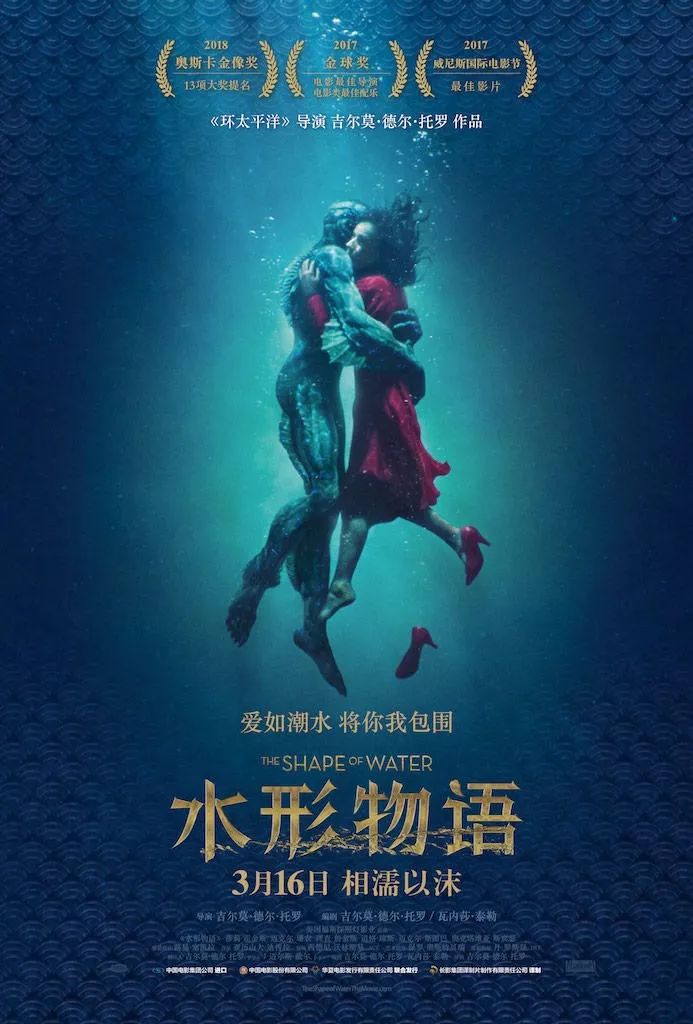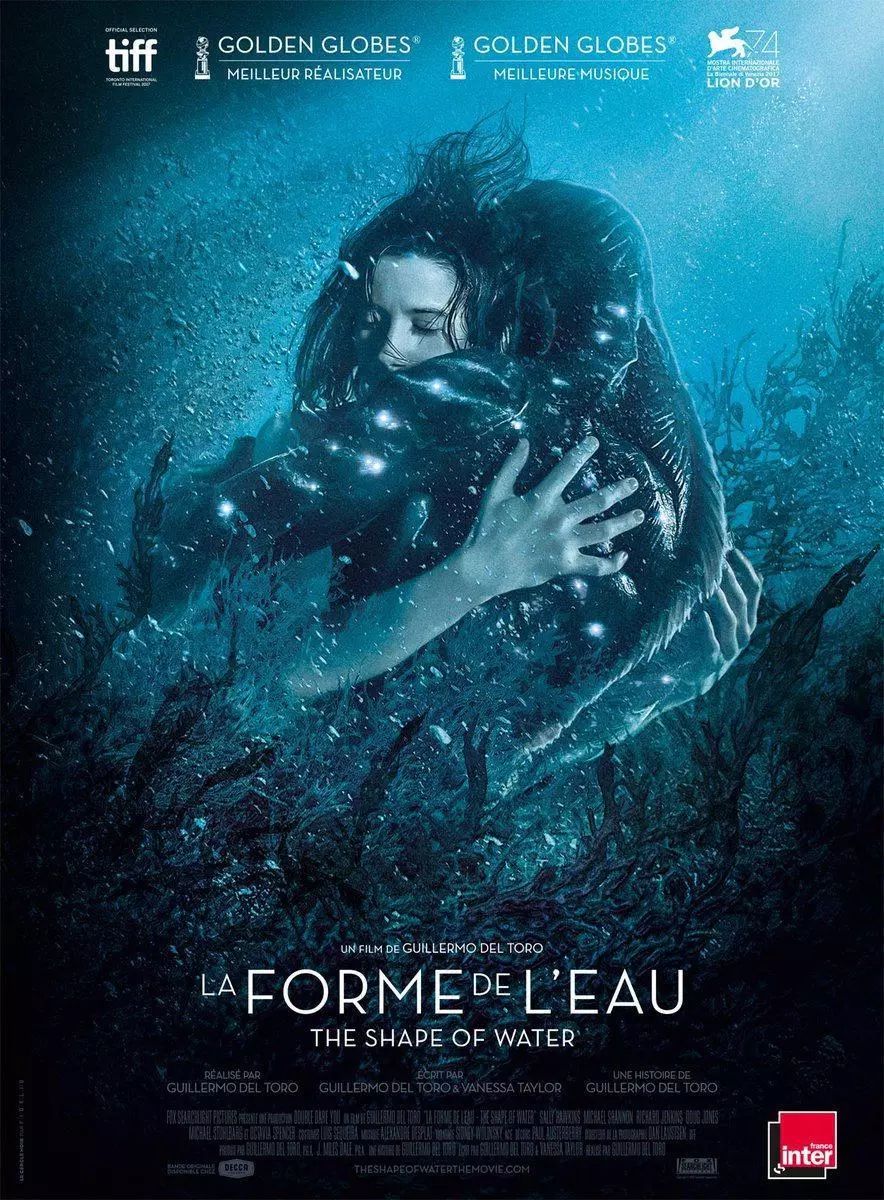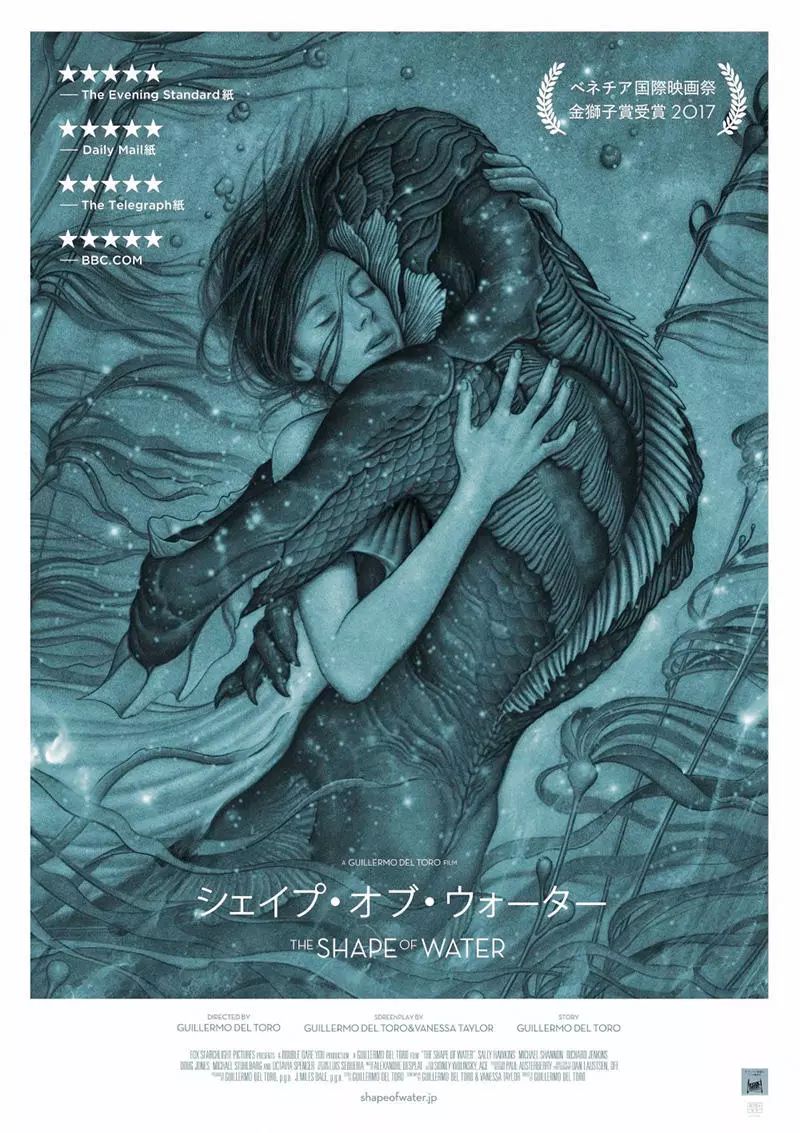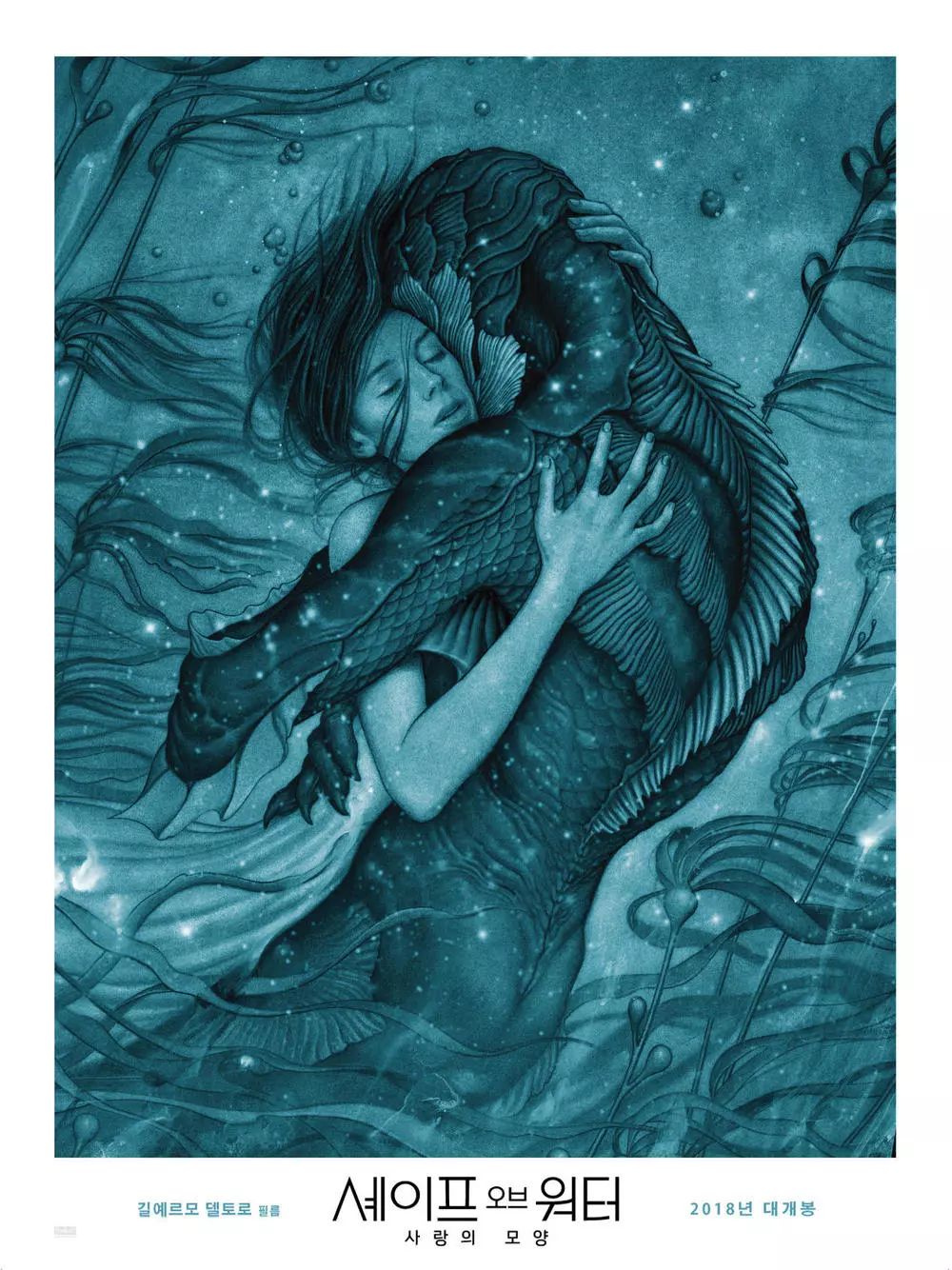
水形物语未删节版这个细节看过才会懂
要说谁是第90届奥斯卡金像奖最大的赢家?毫无疑问的是《水形物语》,《水形物语》以13项奖项提名领跑今年的第90届奥斯金像奖,该片获得了最佳影片、最佳导演、最佳电影配乐和最佳艺术指导4项大奖!
《水形物语》是奥斯卡历届最佳影片中最快引进中国的电影,3月5日奥斯卡颁奖盛典获封最佳影片,3月16日登陆中国院线。
WAIT~~
为什么小编看着这个海报~总觉得哪里不太对…..
于是小编去搜罗了一下各个国家《水形物语》上映的电影海报!
正式版海报——法文
正式版海报——日文
正式版海报——韩文
正式海报——俄文
英文原版海报
小编发现各个国家的海报应用都是无衬线字体,背景画面与文字相融合呼应,使整个画面看起来自然打动人心~感受到影片的唯美质感。文字与画面匹配度相当的高!
Now~呈上中国正式版海报字体图!
此时小编想说,你漂洋过海来到中国的途中到底经历了什么?
小编掐指一算,中文海报字体突变了!!
字体整体重心偏高,横笔画的笔锋做了设计处理,撇捺笔画也做了相应的设计,小编认为初衷应该是想与电影中水中的感觉~人鱼的形象相贴近,表现出黑暗、虚幻的一面。
(小编已经在尽力帮这个字体解释了)
对于海报字体的解析,小编觉得更多的应该先从电影本身出发,知道电影讲的是怎样的一个故事,它想要表现的是什么主题。
文字不仅是传递信息的重要载体,也是设计元素的重要组成部分。既可以当图形化来应用,也可以作为介绍展示。
了解了这些,自然就会对画面和文字搭配有了更准确的把握与认知。
举个两个的例子:
拿观感而言,笔画粗则浑厚、浓重、有力;笔画细则单薄、轻巧、纤弱。
【粗笔画】
变形金刚5——使用字体:汉仪力量黑
粗笔画字体在视觉上会形成高密度的文本块,因为笔画加粗,字体的负空间就会减小,视觉面积加重,产生一种压迫感,使文字形成视觉中心,产生强调的作用。所以粗体字经常用于标题和标语上,占据显眼的位置,产生强调的作用。
【细笔画】
南极之恋——使用字体:汉仪润圆
然而细笔画字体在视觉面积上较淡较轻,稳重,优雅,布白均匀,较小的视觉分量亦不会让读者产生压迫感。
关于字体的运用问题上,小编拙见首先要培养良好的字体感觉,对各类字形足够敏感,了解各种字形的特性风格,应用时才能映衬主题对字体的气质特性把握得恰到好处,所以特别是海报类设计,选好字体至关重要~
分享几款电影海报中西文对比
神偷奶爸3
黑 豹
古墓丽影
三块广告牌
综合以上介绍和不同海报的中西对比,是否对大家关于海报的字体应用有了一点点的启发呢?
电影《水形物语》导演托罗在一次采访中说到,其实一开始剧本的名字叫做《艰难时日的童话》。这个名字更具有现实隐喻,他想表达的是“关于人与人之间的联系,关于同理心,关于人们需要彼此支撑、彼此依靠才能够幸存。”
小编认为海报设计也是一样,文字与画面相呼应,彼此依靠融合,才能共同呈现出完美的作品。
我拥抱着爱从梦中醒来~你执着地等待却不曾离开!